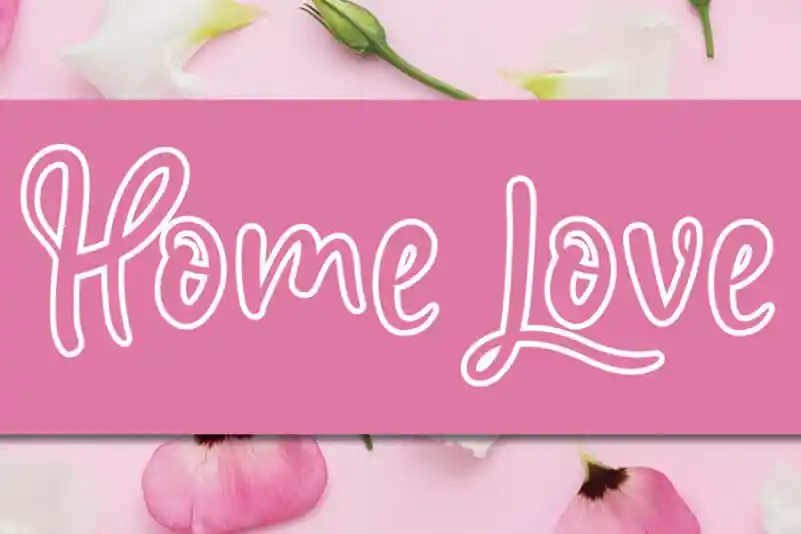
Home Love Script Font – Download Grátis
Home Love Script Font é uma elegante fonte criada à mão, cheia de delicadeza e magia. Ideal para incrementar diversos projetos de design ao nível mais alto, seja branding, subtítulos, designs de casamentos, convites, assinaturas, logotipos ou até mesmo rótulos. Com uma leveza que transborda elegância, essa fonte é perfeita tanto para a estética moderna quanto para aquelas ideias mais vintage e carinhosas. É ideal para quem busca uma fonte que não apenas destaca o design, mas também traz um toque de amor à cada projeto.